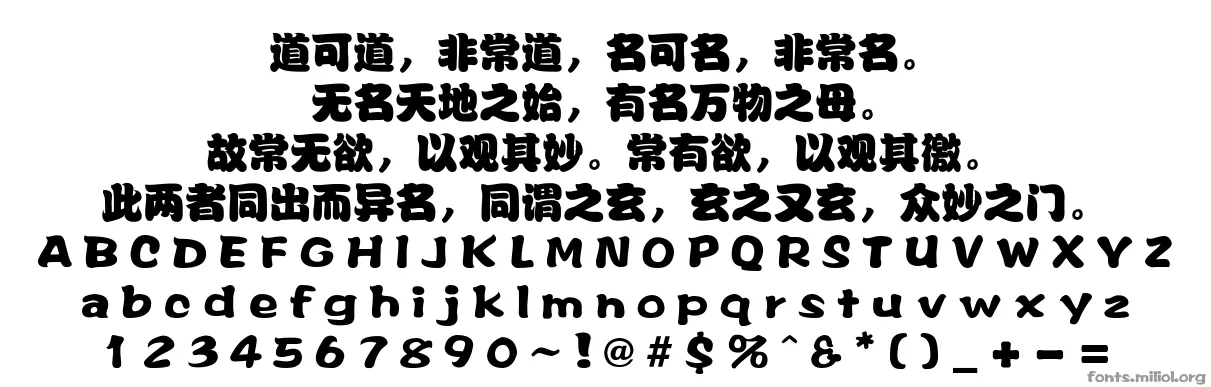
## 方正胖娃简体:童趣与创意的完美融合
方正胖娃简体是一款极具特色的中文字体,由方正字库精心设计。这款字体以其圆润饱满的笔画和活泼可爱的造型,在众多字体中脱颖而出,成为设计师和创意工作者的心头好。
该字体的设计灵感来源于儿童涂鸦,每个笔画都经过精心雕琢,呈现出独特的艺术美感。字体的圆润造型不仅给人以亲切感,更传递出温暖与欢乐的氛围。在笔画处理上,设计师巧妙运用了粗细变化,使字体在保持整体协调性的同时,又富有层次感。
方正胖娃简体的应用场景十分广泛。在儿童读物、教育类出版物中,它能营造出轻松愉快的学习氛围;在创意广告设计中,它能为作品增添趣味性和亲和力;在品牌形象设计中,它更是打造年轻化、个性化品牌形象的利器。
这款字体的独特之处在于它完美平衡了艺术性与实用性。设计师在创作过程中,既注重字体的艺术表现力,又充分考虑其在实际应用中的可读性和适用性。这种平衡使得方正胖娃简体不仅是一款优秀的艺术字体,更是一件实用的设计工具。
在数字化时代,字体设计已经成为视觉传达的重要元素。方正胖娃简体的出现,为设计师提供了更多创意可能,也为中文排版注入了新的活力。这款字体不仅展现了中文字体设计的创新精神,更体现了传统文化与现代设计的完美融合。